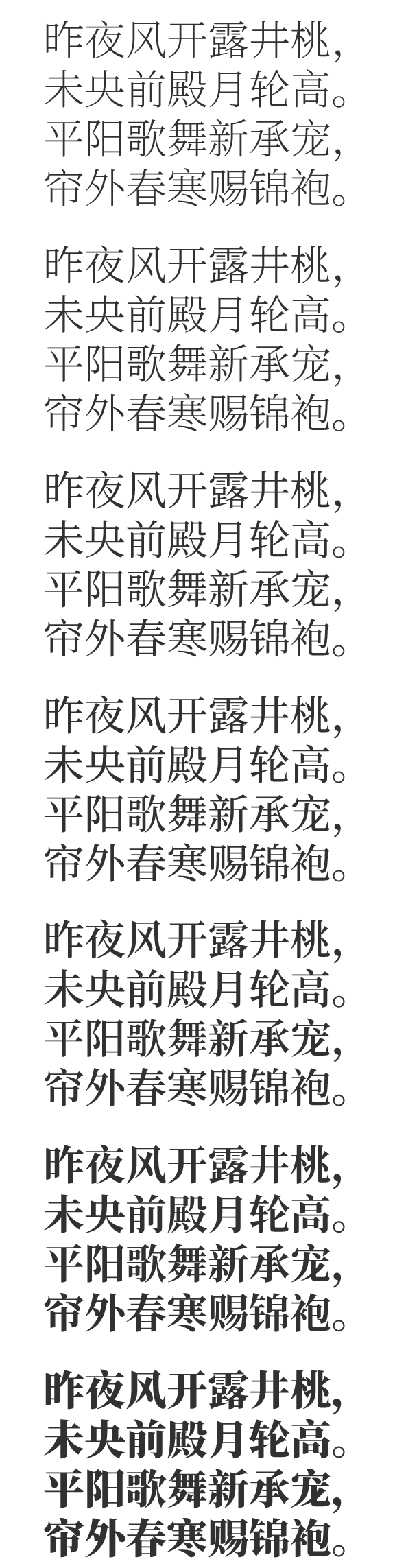
思源宋体
思源宋体介绍
继思源黑体之后, Adobe与谷歌又一款开源泛中日韩字体——思源宋体于今天4月4日正式发布。
思源宋体是 Adobe Type 发布的最新泛 CJK 字体,它是对应于思源黑体的宋体字体;我们发布这两种字体是为了响应统一设计的需求,以服务于东亚 15 亿人口。
思源宋体支持四种不同的东亚语言(简体中文、繁体中文、日语和朝鲜语),7 种粗细类型中的每一种都有 65,535 个字形,可共同呈现一致的视觉美感。该字体还包含多个西方字形,支持拉丁语、希腊语和西里尔文脚本,这些字形均来源于 Source Serif。